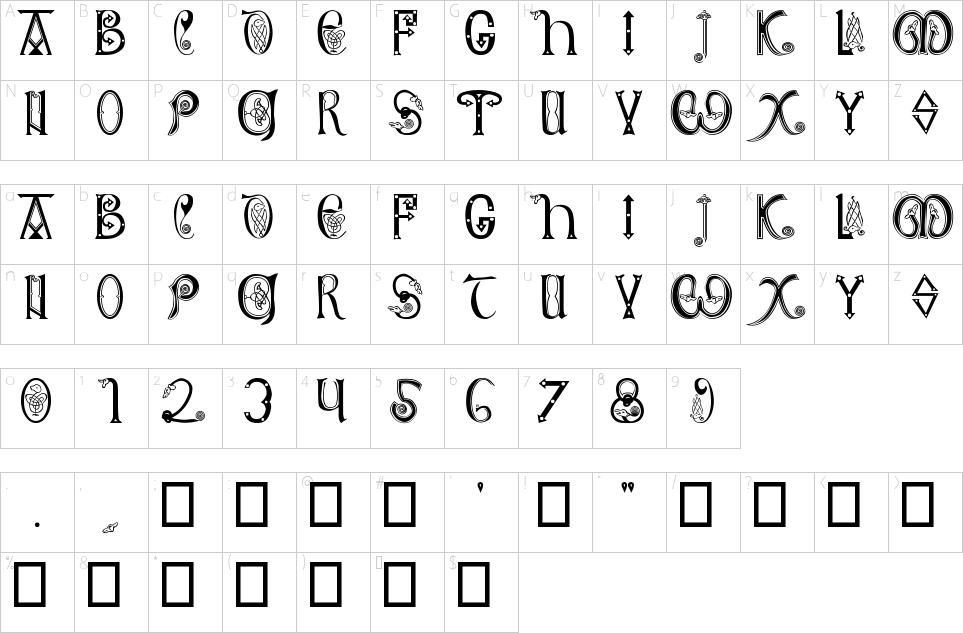
Anglo Saxon Font
A fonte ‘Anglo Saxon’ é uma criação de Robert Anderson – Flight of the Dragon, disponível gratuitamente tanto para o sistema Windows quanto para o Mac. Ela foi projetada para trazer a elegância e a força característica das fuentes anglo-saxônicas, que têm sido essenciais para marcas de todo o mundo ao longo dos séculos. Com seu design sóbrio e poderoso, a ‘Anglo Saxon’ é ideal para uso em materiais de marketing, design editorial e em qualquer aplicação onde um estilo tradicional e confiável seja desejado. Esta fonte tem sido uma escolha popular entre designers e usuários, tendo sido baixada mais de 14.885 vezes. Se você está procurando uma fonte que traga um toque de elegância e força ao seu design, a ‘Anglo Saxon’ é uma fonte perfeita para adicionar ao seu portfólio.